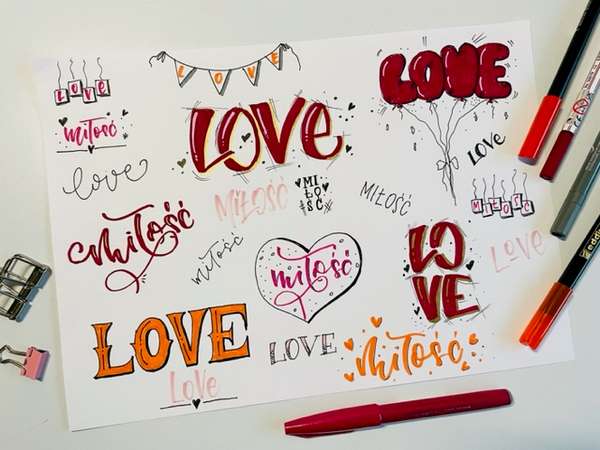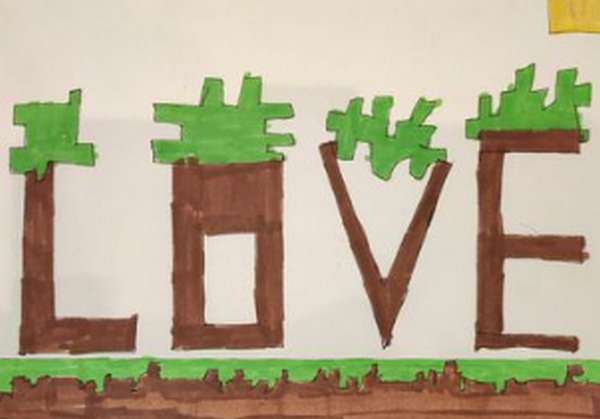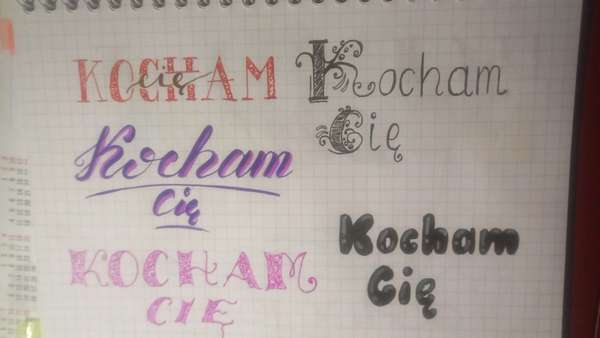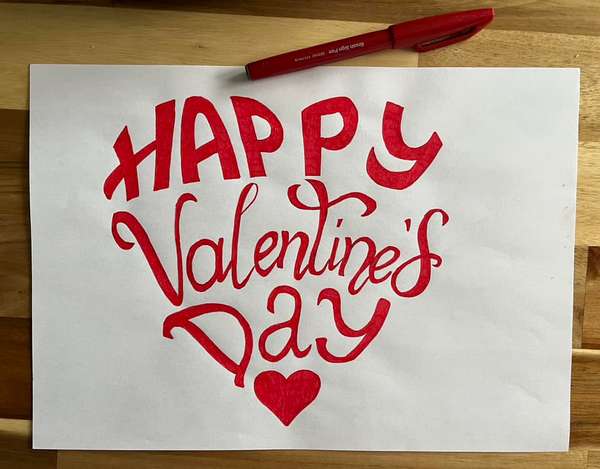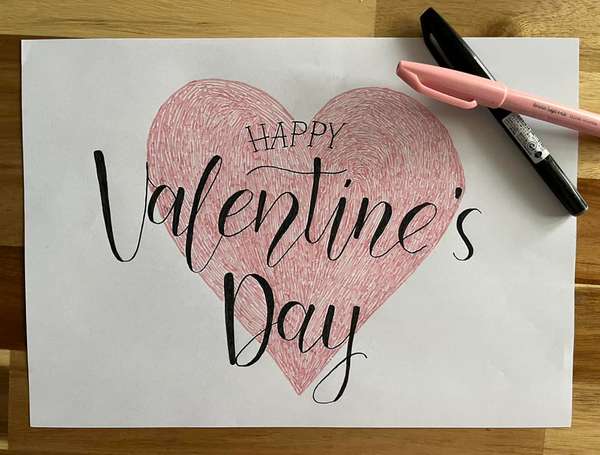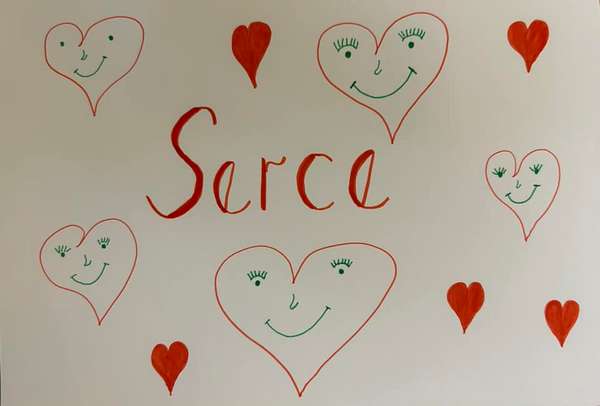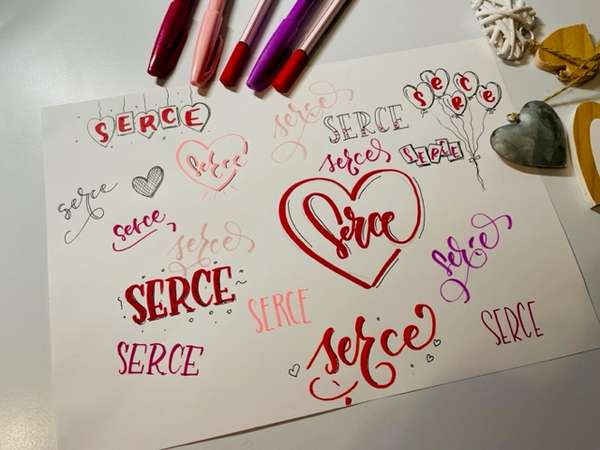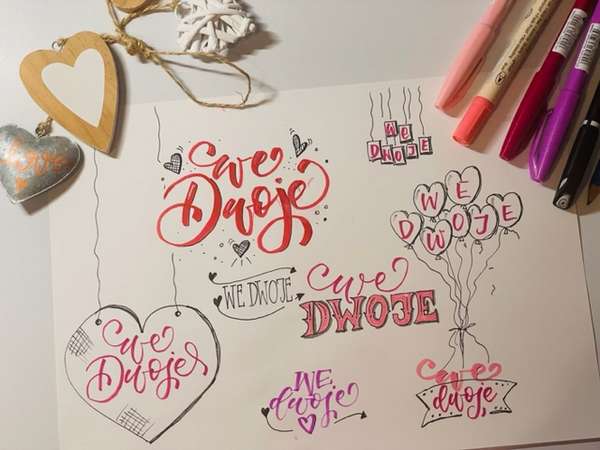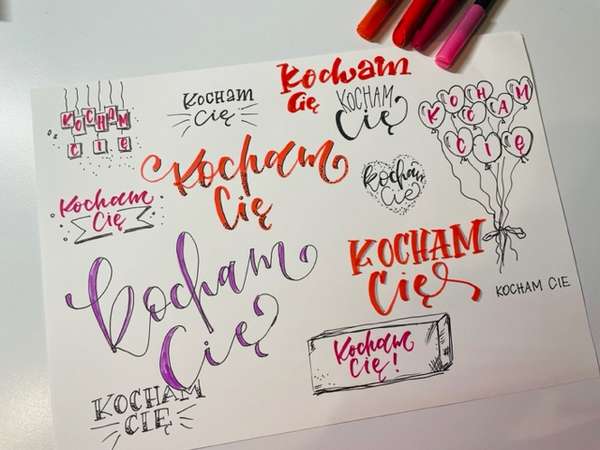
Walentynki i miłosny lettering – przegląd prac
Mimo że „wyrosłam” już dawno z walentynek nie mogę przepuścić żadnej okazji malowania fajnych ciekawych letteringów okazjonalnych. Czy to halloween, walentynki chętnie chwytam za brush peny i lubię eksperymentować z literami. Tak było i w tym roku. Miłosny lettering to temat przewodni lutego. A, jako że dopiero co skończył się nasz 4 tygodniowy kurs hand letteringu i rozkręciłam się w dekorowaniu liter, postanowiłam przygotować kilka wersji jednego słowa.
Walentynki – czerowny lettering
W tym roku postawiłam na czerwony minimalizm. Podczas 4-tygodniowego kursu pokazywałam proste kroje do wykorzystania, dlatego w moich walentynkowych pracach pojawiał się ten sam motyw przewodni podczas konstrukcji liter.
Korzystałam podczas kompozycji z prostych figur geometrycznych, a w krojach dominował prosty brush lettering i proste szeryfowe litery.
Przegląd prac letteringowych z facebooka
Zarówno na moim fanpage’u, jak i w grupie na facebooku pojawiły się prace walentynkowe. Oto kilka przykładów:
Praca Marceliny K.
Praca Klaudii K.
Praca Aliny Cz.
Praca syna Pauliny A.
Praca Pauliny A.
Praca Marty Z.